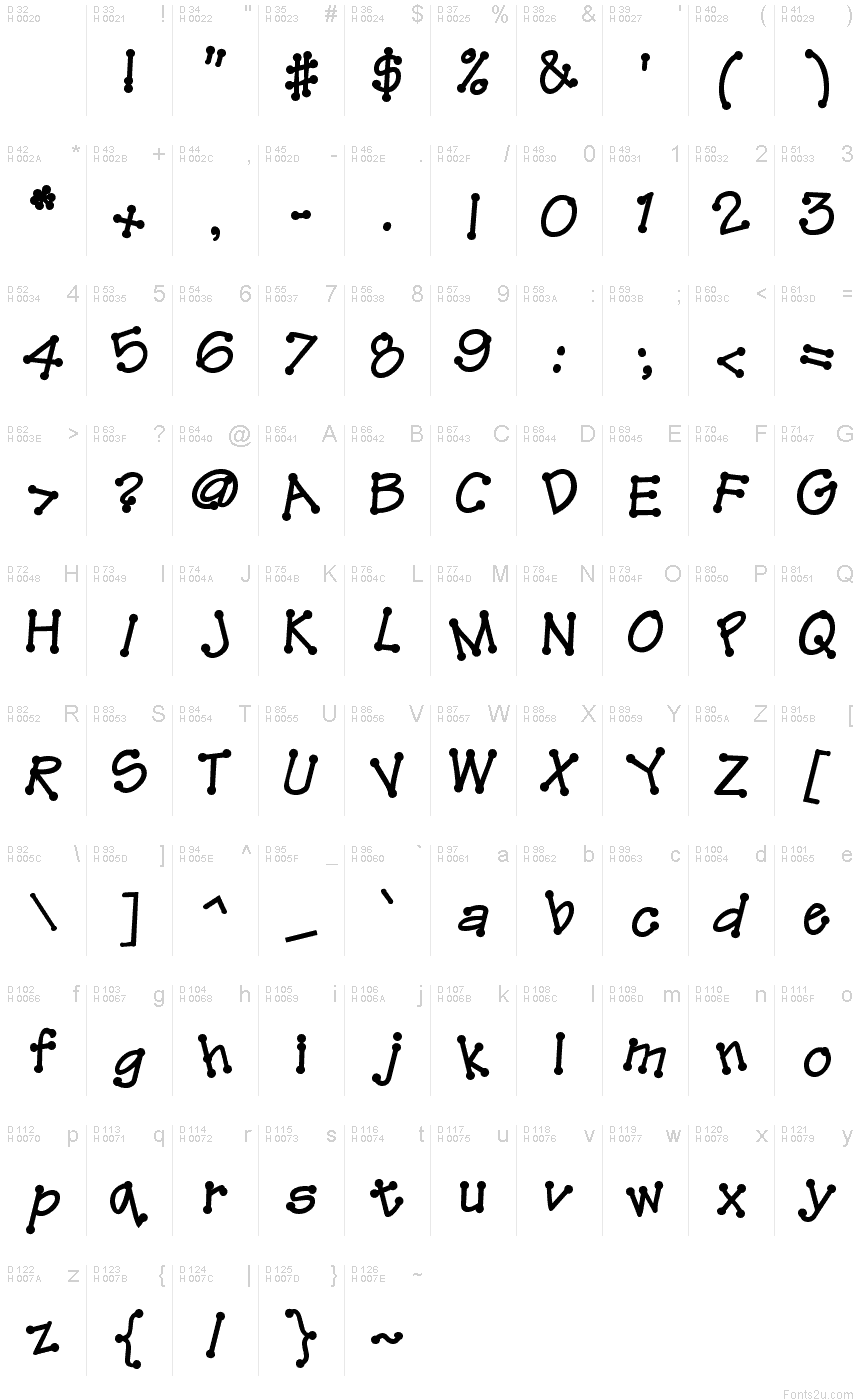
ThreadFun BoldItalic، هو خط عرض مجاني من تصميم كريس ماكغريغور عام 1993، يحول الحروف إلى خيط مرح مشدود بإحكام بين رؤوس دبابيس مستديرة. تبدو الأشكال مائلة ومرسومة باليد مع القليل من التعرج، وتجعل الحلقات والأطراف المتدلية من الخط يبدو كأنه عمل فني من الخيوط بدلاً من مجرد حروف عادية.
هذا يجعله خياراً مثالياً لملصقات الأطفال، والعلامات التجارية الخاصة بالحرف اليدوية، وعناوين سجلات القصاصات، ودعوات الحفلات، والتغليف غير التقليدي، حيث تقوم فكرة "أدوات الخياطة" بالجزء الأكبر من العمل البصري. وبما أنه خط مجاني، فهو مناسب أيضاً للعناوين القصيرة وتصاميم الأغلفة والبطاقات التي تحتاج إلى لمسة يدوية دون فقدان وضوح الحروف.